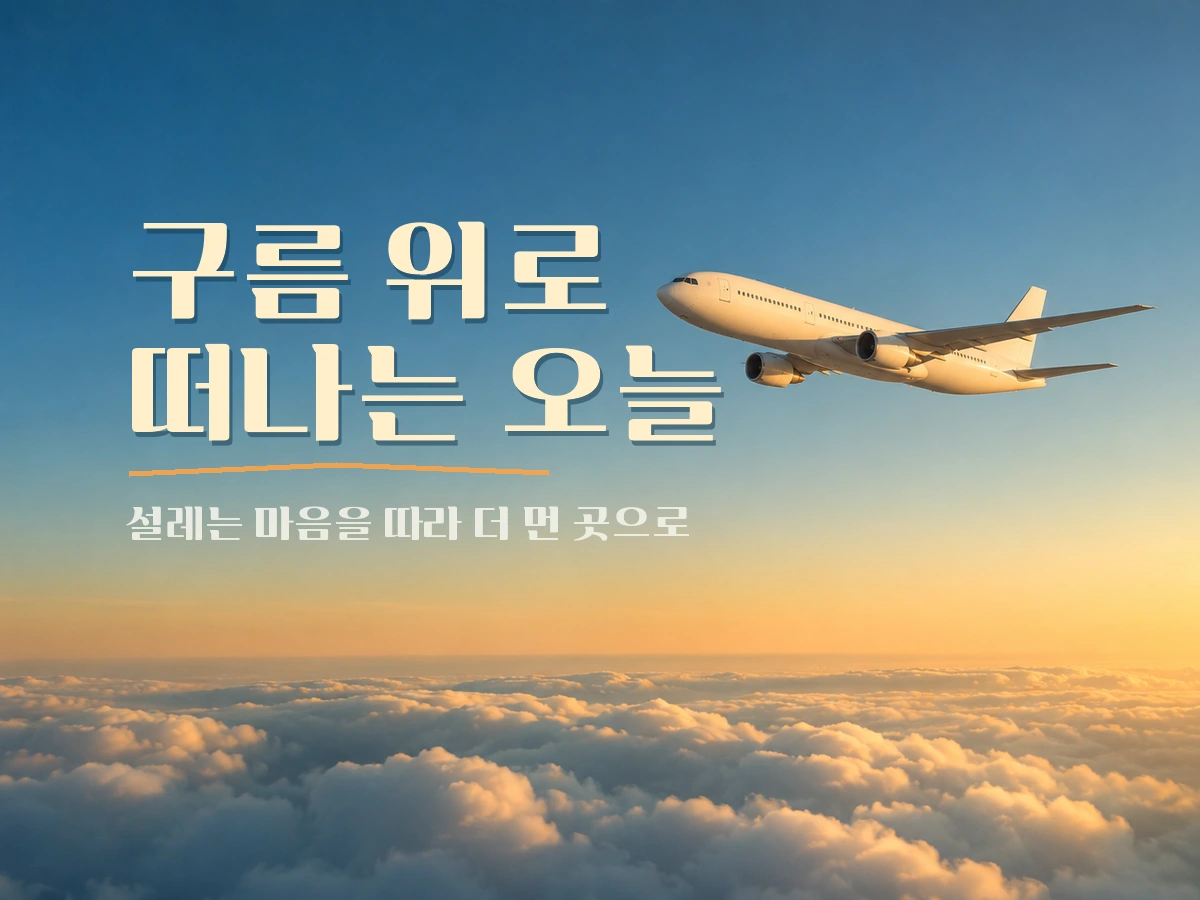
티웨이 하늘체 — 티웨이 X 폰트랩(주)에서 배포하는 무료 폰트입니다. 붓끝의 세리프와 독특한 내리점이 어우러진 레트로 감성의 장식체
티웨이항공 서체 세 벌 가운데 본문을 맡는 쪽입니다. 2021년 3월에 폰트랩과 함께 공개됐습니다.
제작사 설명이 구체적입니다. 뚜렷하고 밝은 인상의 직선 본문용 서체로 특징을 절제해 모임꼴의 공간감과 가독성을 높이는 디자인으로 제작했다고 밝혔습니다. 특징을 절제했다는 말이 핵심입니다. 제목용인 항공체가 초성을 키워 존재감을 냈다면 이쪽은 반대로 개성을 덜어내 읽기에 집중하게 만들었습니다.
브랜드와 이어지는 디테일도 하나 있습니다. 티웨이 로고의 아포스트로피와 비행기 터보팬을 회전시켜 만든 자소 내리점이 특징이라고 설명합니다. 굵기는 하나뿐이라 제목과 본문을 굵기로 나눌 수 없으니, 제목은 같은 가족의 항공체나 날다체에 맡기는 것이 설계 의도입니다. 폰트픽이 서비스하는 파일은 현대 한글 11,172자를 모두 담았습니다.